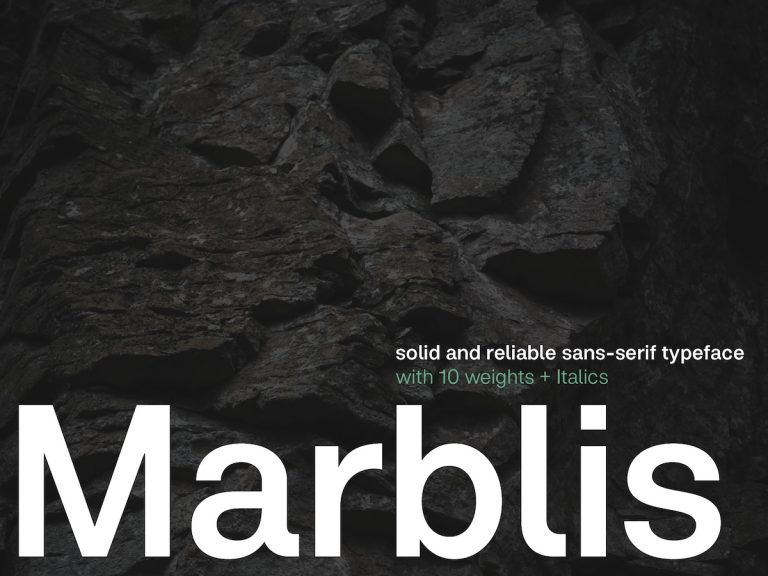
Warm, weich & ein Fels in der Brandung: Die Marblis
Auf der Suche nach einer Alternative zu der omnipräsenten Helvetica blieb die Strategie schnell auf der Stecke, die Leidenschaft des Artdirectors und Typedesigners Julien Fincker für klassische Grotesk Schriften übernahm und so entstand die Marblis. Noch ist sie mit Rabatt erhältlich.
Ein Alleskönner sollte der neue Font sein. Eine Antwort auf die Helvetica, klar und neural – und mit einer breiten Palette an Zeichen, Sprachen und Features, die die Schrift zu einer zuverlässigen Wahl werden lässt.
Doch kaum hatte Julien Fincker, der als Artdirector und als Typedesigner samt seiner Foundry Font Cuisine nahe Stuttgart lebt, mit dem Zeichnen der neuen Schrift begonnen, rückte die Helvetica in die Ferne.
Stattdessen übernahm seine Leidenschaft für klassische Grotesk Schriften und der Anspruch, eine neue Schrift zu entwickeln, die zwar stabil und solide ist, aber dabei keineswegs technisch und kühl wirkt.
Dafür ließ er eine durchdachte Konstruktion und ausgewogene Zeichenbreite auf geradlinige Ausläufe wie beim »t« oder »f« treffen – und auf weiche Kurven und sanfte Ausläufe wie beim »a« oder »l«.
Stabil – und für alle Eventualitäten
So entstand schließlich die Marblis, deren Name für Julien Fincker auf der Hand lag.
Da Marblis an Gesteinsformen erinnert und für ihn die Schrift »wie ein Fels in der Brandung« ist, ein Fundament, auf das man bauen kann, egal, auf welche Herausforderungen man trifft.
Und das nicht nur mit einer erweiterten Sprachunterstützung, sondern auch mit vielen hilfreichen Features und Sonderzeichen.
Dazu gehören schreibbare Pfeile und Zahlen in Kreisen und Quadraten, zahlreiche Währungs- und hoch- und tiefgestellte Zeichen. Und so stieg deren Zahl schnell auf mehr als 1400 an.
Mit zehn Schnitten von Thin bis Black und inklusive Kursiven, ist sie für Julien Fincker besonders auch für Corporate Design, für Editorial Design und für Leitsysteme geeignet. Sie wirkt stabil und solide und verfügt gleichzeitig über mitreißende kleine Eigenheiten wie dem ausgeprägten Auslauf beim »a« und bei all ihrer Klarheit über eine ganz eigene Wärme.